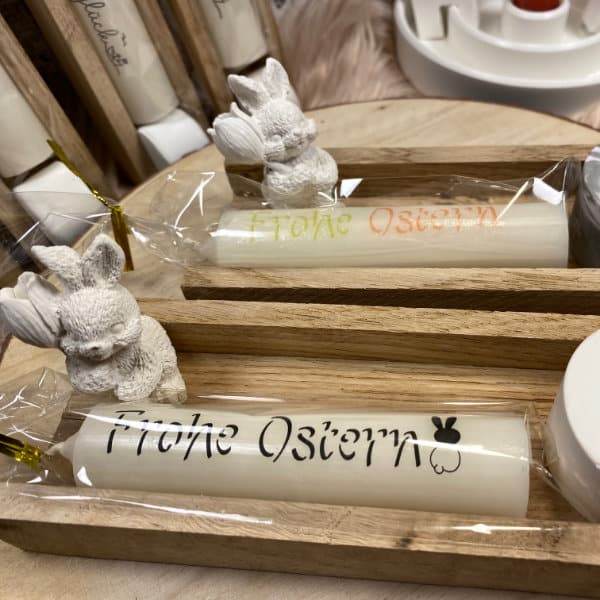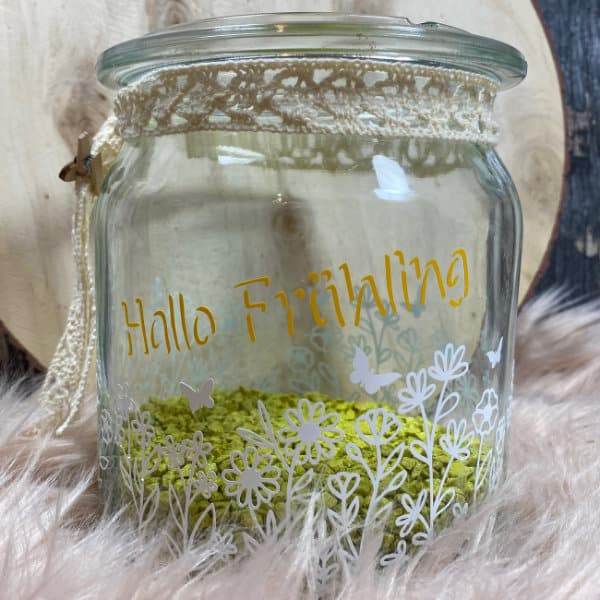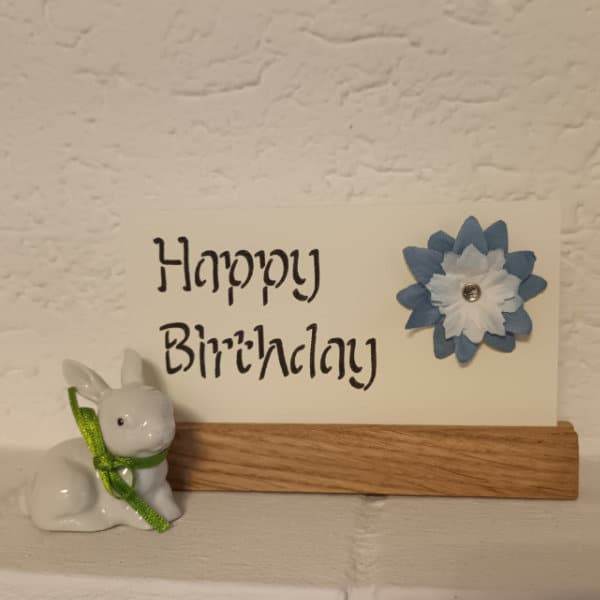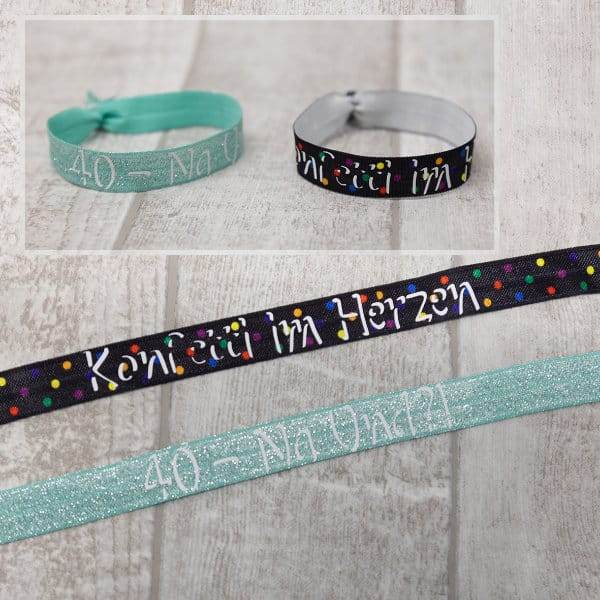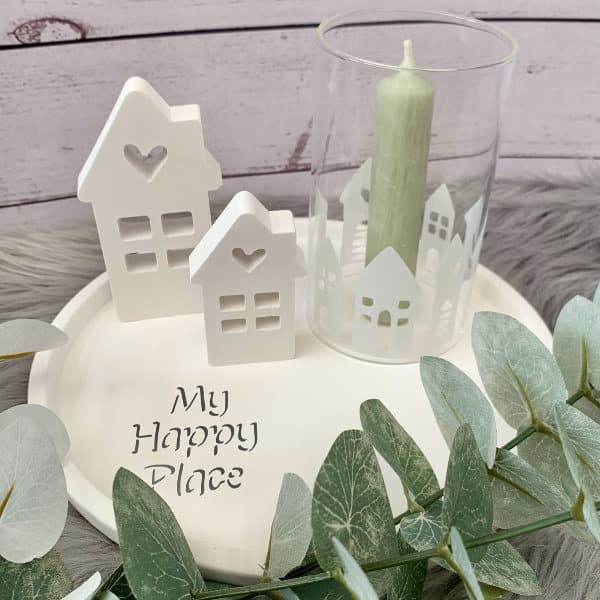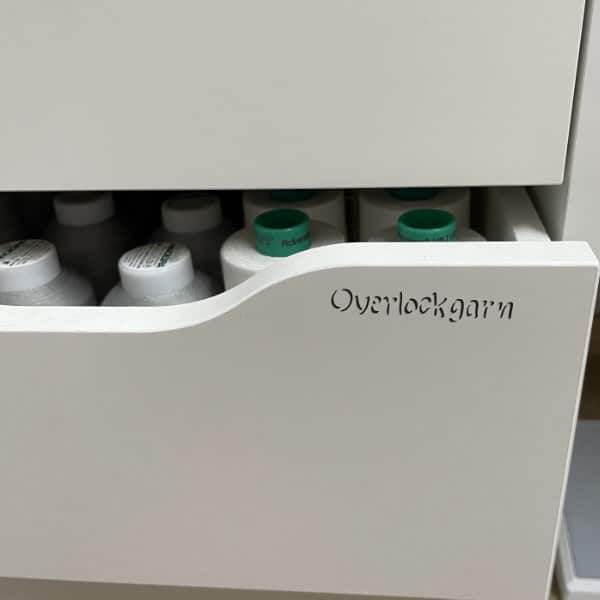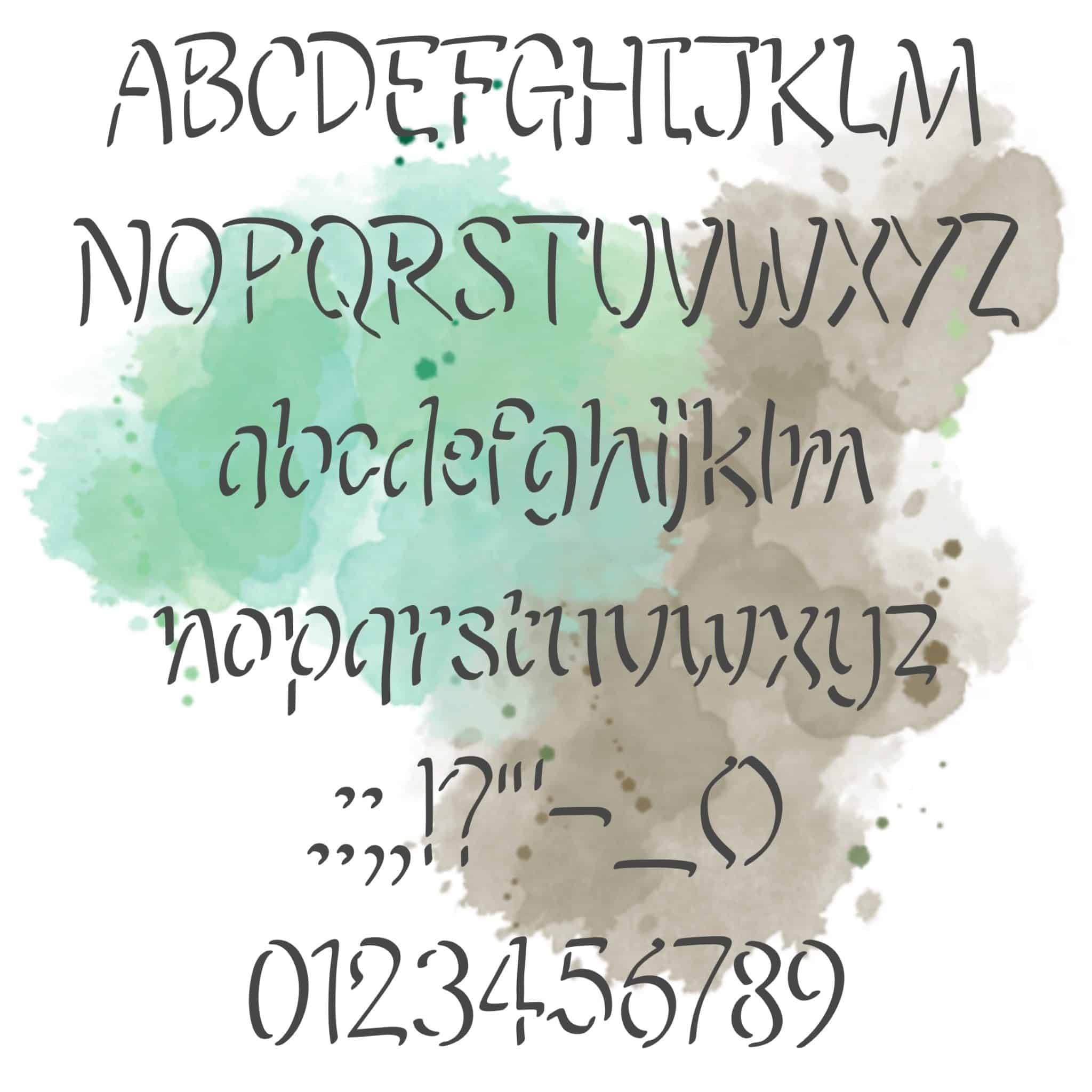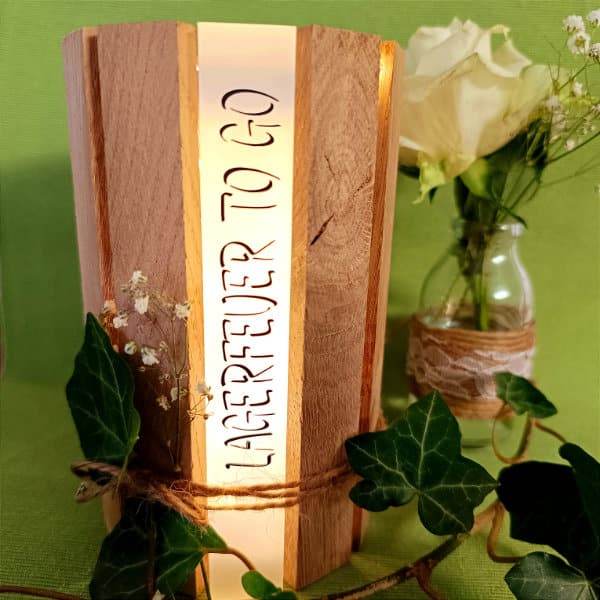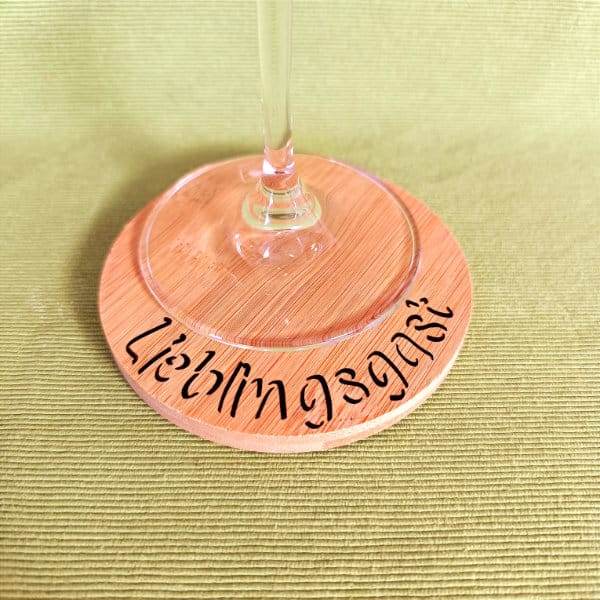
Shadow Stencil | OTF Schriftart
Die Shadow Stencil Schriftart verleiht deinem Text eine kühne und dynamische Ästhetik. Mit ihrem einzigartigen Design werden die Buchstaben und Zeichen durch Schatten dargestellt, was einen faszinierenden visuellen Effekt erzeugt. Diese Schriftart eignet sich perfekt für Plakate, Werbung und kreative Projekte, die nach einem markanten und modernen Look suchen. Gib deinem Design mit Shadow Stencil einen Hauch von Originalität und Persönlichkeit.